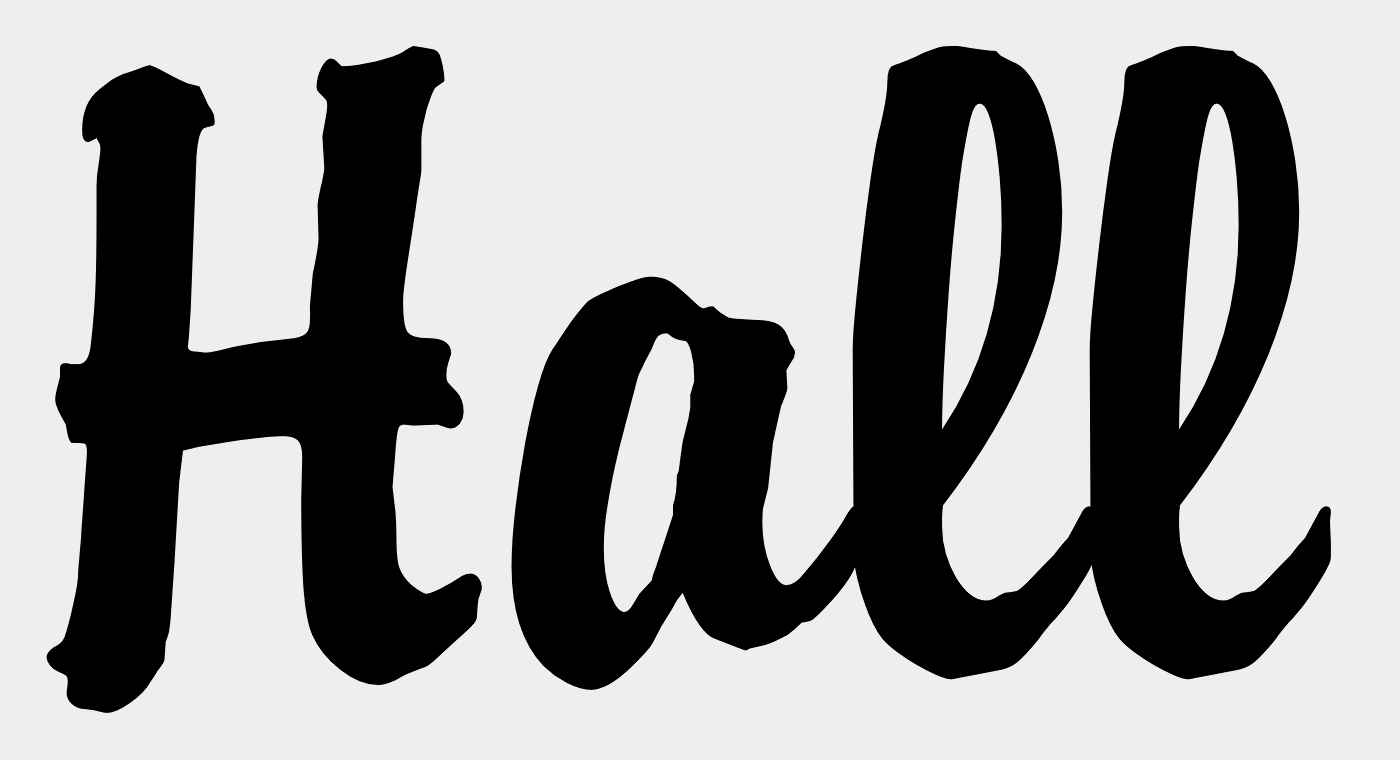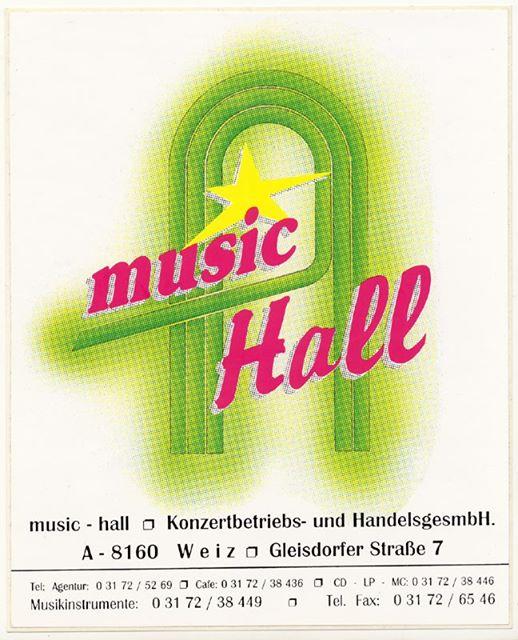
Bitte um Hilfe, welche Schrift
☞  Ich suche bitte die Schirft von "music-Hall"
☞ zirka 1990
☞ Ich suche bitte die Schrift von "music-Hall"
"music" ist allerhöchstwahrscheinlich eine schräggestellte ("Falsche Kursive") ITC Souvenir Bold.